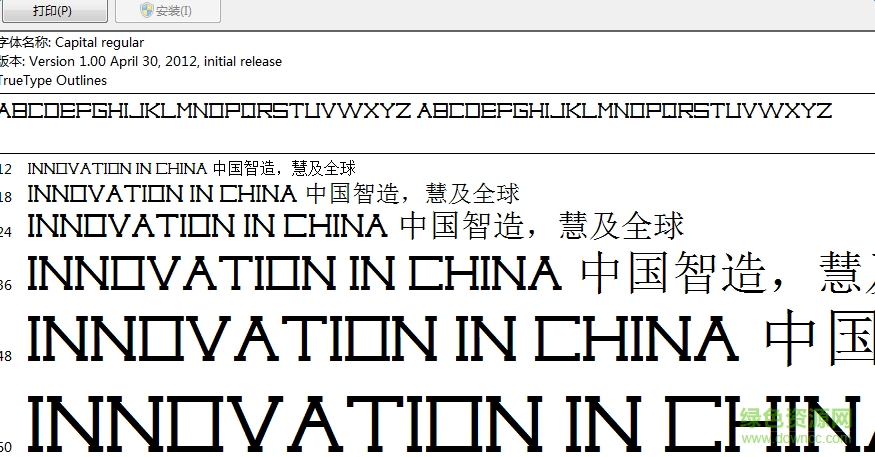
capitalsregular字體是一款英文字體庫(kù)中的個(gè)性字體,該字體可以適用于產(chǎn)品包裝、廣告宣傳、出版印刷、商標(biāo)用字、商業(yè)網(wǎng)站、影視影像視頻、書籍出版印刷等,有需要的朋友可以免費(fèi)下載收藏。
capitalsregular字體給人一種線條美,英文都是由直線組成,簡(jiǎn)介明了,讓人一眼就能認(rèn)清!有需要的朋友趕快來(lái)綠色資源網(wǎng)下載使用吧!